Алфавит русский красивым шрифтом – Русские шрифты | Шрифты онлайн
25 красивых шрифтов русского алфавита
Если Ваша деятельность связана с дизайном, то подборка шрифта для какого-либо проекта является важной составляющей вашей работы. Этому процессу стоит уделить большое значение. Удачно подобранный шрифт быстро располагает и заинтересовывает любого человека. Для многих читателей, красота шрифта важнее, чем содержание написанного. Шрифт помогает быстрее ориентироваться в тексте и расставлять нужные приоритеты.
Бывают случаи, когда журнал, статья в интернете или рекламный щит становятся неинтересны читателю, по причине неудачно выбранного шрифта. Люди не станут воспринимать информацию, которая отталкивает их и вызывает плохое впечатление.
Несколько лет назад, американские ученые провели эксперимент на данную тему. Участникам эксперимента предлагалось ознакомиться с материалами, написанными на различную тематику. Одни статьи были оформлены неудачно подобранным, непривлекательным шрифтом, с плохим подбором картинок. Для оформления других использовались самые лучшие красивые шрифты с прекрасными пейзажами, но в их тексте содержались различные непристойные выражения. И что вы думаете? Приборы показали, что реакция отторжения и негатива к полученной информации была приблизительно одинаковой.
Основными характеристиками шрифта являются гарнитура, пропорции, насыщенность, контрастность, начертание и наклон. По этим свойствам стоит подбирать необходимый, для Вас.
- Гарнитура – объединение шрифтов, связанных общим стилем
- Пропорции – изменение ширины в сфере одной гарнитуры
- Насыщенность – изменения толщины штрихов одноименных знаков
- Контрастность – отношение толщины штрихов к толщине основных знаков
- Начертание – комплект всех символов шрифта
- Наклон – определенный угол расположения знака
Итак, рассмотрим 25 самых красивых и интересных шрифтов русского алфавита, которые могут стать для Вас полезными.
– Разработчиком данного шрифта является Vincent Connare. Шрифт отлично доработан в каждой детали. Данный шрифт не имеет засечек. Присутствует поддержка русского алфавита. Предназначен для удобной читабельности с экрана.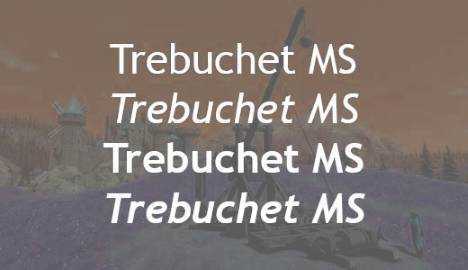
Reef
– приятный русский шрифт, имеющий скругленные границы. Очень подходит для сайтов использующих скругленные линии. Его плюсы в простоте и конструктивности. Также шрифт является свободным для пользователей
Cyrillic Old
– симпатичный шрифт с нотками древнеславянской письменности
Gost
– один из лучших шрифтов для работы с чертежами в программе AutoCad и во всех подобных программах.
Uni Suns
– отличный шрифт, не имеющий засечек. В данном шрифте используются исключительно заглавные буквы. Дизайнер – Святослав Симов (Компания Fontfabric).
Helvetica
– в нашей современности данный шрифт использует любой дизайнер. Шрифт представляет класс нео-гротеск. В арсенале имеются как математические, так и псевдографические символы. Helvetica трудится над разработкой логотипов BMW, Nestle, Motorola, Toyota, Samsung и т.д. Данный шрифт заслужил почетное звание самого перспективного.
Panton
– шрифт имеет 34 начертания с большим набором иконок. Шрифт является достаточно редким, но очень интересным по наполнению.
Open Suns
– шрифт 14-ти начертаний. Достаточно часто используется в дизайне интернет — сайтов. Разработчик – Стив Мэттисон. Отличается дружественной внешностью и удобочитаемостью для мобильных устройств. В основном используется на смартфонах платформы.
Burford
– один из лучших акцидентных шрифтов современности. Лучшее решение для оформления визитных карточек и других компонентов дизайна. Шрифт представлен в 18 начертаниях.
Arkhip
– отличная работа русских дизайнеров – Ивана Климова, Ирины Деменьтевой, Алексея Архипова, Анастасии Бушковой и других. Достаточно редкий, выделяющийся из общей массы шрифт.
Barkentina
– дизайнер – Кирилл Златков. Используемый стиль шрифта – арт-деко. Очень удобен для применения печатных материалов.
K141
– шрифт создан не так давно — в 2014 году. Шрифт без засечек и использует только заглавные буквы.
Cony
– декоративный шрифт с использованием растянутых букв.
Bebas Neue
– русскоязычный шрифт. Особенностью шрифта является растяжка букв в вертикальном направлении.
Danger
– шрифт очень удобен для создания трафаретов.
Iron Russian Edition
– создан на базе известного шрифта Iron. Выделяется своим интересным дизайном.
Nise SEGA Cyrillic
– шрифт оформлен в стиле видео — приставки SEGA.
Movie Letters Cyrillic
– разработан для использования в фильмах для создания титров.
Neon
– отлично подойдет для проектирования вывесок магазинов, баров и т.д. Шрифт выполнен в неоновом стиле.
AC Line
– качественный шрифт для использования в чертежах.
Tkachevica
– действительно красивый шрифт пиксельной тематики.
Capitalist
– жирный шрифт. Напоминает шрифты советского времени.
Lloyd Serif
– необычный шрифт с закругленными буквами.
Illusing Grotesque
– красивый, стильный, тонкий шрифт с засечками.
Ralev
– симпатичный шрифт с закругленными буквами.
Как мы видим, разновидностей удивительных и нестандартных шрифтов — большое количество. Выбор за Вами.
owro.ru
Красивые печатные буквы русского алфавита для оформления
Предлагаем вам красивые печатные буквы русского алфавита для оформления праздника, Дня Рождения, декора стен в детской комнате, для обучения детей буквам. Буквы можно распечатать на цветном принтере, либо воспользоваться черно-белым шаблоном букв и разукрасить готовые буквы вместе с ребенком. Черно-белые буквы можно распечатывать на цветной бумаге или картоне. Нажмите на букву — она откроется в полном размере, после чего ее можно распечатать. Также все представленные алфавиты доступны для скачивания отдельными архивами.
Черно-белые печатные буквы русского алфавита. Скачать архив (Печатные буквы.zip, JPG, 407 Кб)
Красные печатные буквы русского алфавита. Скачать архив (Красные печатные буквы.zip, JPG, 2.2 Мб)
Еще один интересный набор черно-белых печатных букв русского алфавита. Картинки кликабельны. Скачать архив (Черно-белые печатные буквы.zip, JPG, 1.02 Мб)
maminy-sekrety.ru
Шаблоны букв для вырезания
Очень часто в практике школ, детских садов и развивающих центров при подготовке к различным праздникам, для украшения стендов используются шаблоны букв русского алфавита для вырезания из бумаги.
Где и с какой целью могут быть применены шаблоны?
При подготовке тематических вечеров, утренников, детских праздников часто требуется подготовить стенгазету, объявление, оформить выставку детских работ и сделать к ним подписи и т.д. Вся эта организация требует быстрого и четкого оформления с помощью букв русского алфавита. Благодаря шаблонам для вырезания из бумаги эта проблема решается в короткое время. Стоит только приложить шаблон к бумаге нужного цвета, обвести и вырезать, а затем наклеить в необходимое место. В результате готова красивая и ровная надпись.
Где можно достать шаблоны букв алфавита?
Их можно купить в любом канцелярском магазине, однако если дома есть интернет, вы легко можете скачать их совершенно бесплатно с нашего сайта, распечатать и использовать в работе. Таким образом, шаблоны букв для вырезания из бумаги будут полезны, учителям, воспитателям детских садов и развивающих центров.
Однако это далеко не все применение шаблонов алфавита. С их помощью родители могут самостоятельно научить ребенка читать, заинтересовать изучением букв. Вместе с ребенком вы можете вырезать буквы из бумаги, наклеивать на основу или на кубики, составлять слова. Малыш может вырезать буквы из бумаги того цвета, какой он захочет. Так дети лучше усваивают материал, запоминают алфавит, с удовольствием учатся читать и писать.
Шаблоны для вырезания можно использовать для аппликаций. Малыши учатся аккуратно наклеивать вырезанные буквы на бумагу, тренируют усидчивость, внимательность. Если вы занимаетесь с детьми дошкольного возраста, следует соблюдать технику безопасности. Лучше не давать ножницы в руки маленьким детям: буквы вырезают взрослые, а наклеивать могут дети. Вместе с малышами благодаря шаблонам можно готовить праздничные открытки для родственников, поздравления, украшать и подписывать подарки.
Материалы для скачивания
Скачать бесплатно шаблоны букв для вырезания можно здесь.
Вы также можете скачать синий алфавит со знаками препинания и цифрами единым архивом здесь.
Все буквы русского алфавита со знаками препинания и цифрами.
Шаблоны букв русского алфавита на прозрачном фоне по мотивам мультфильма «Маша и медведь.»
Чтобы скачать красные шаблоны букв со знаками препинания, нажмите на эту картинку.Нажимайте на картинки ниже, скачивайте и распечатывайте нужную Вам букву:
Итак, шаблоны букв русского алфавита могут быть весьма полезны не только учителям, воспитателям, но и родителям, которые занимаются развитием своих детей самостоятельно. Шаблоны используются для подготовки праздничных надписей, как для общественных мероприятий, так и для домашнего пользования. Вырезанные буквы полезно применять на уроках труда в качестве аппликаций, для занятий с дошкольниками, для изучения букв русского алфавита и формирования навыков чтения. Шаблоны можно скачать совершенно бесплатно на нашем сайте, распечатать и использовать в работе по своему усмотрению. Они наверняка помогут вам успешно подготовить детей к школе, развить интерес к знаниям.
Похожие статьи
Загрузка…steshka.ru
Красивый почерк алфавит на русском, английском языке (Фото)
Почерк, как умение рисовать, — своего рода искусство. Часто человек не может понять собственного почерка, например, при быстрой диктовке. Сегодня правильное и понятное письмо отходит на второй план, уступая место электронным документам. Но есть ситуации, когда письменная речь должна быть понятна и разборчива. Как исправить почерк и сделать его красивым, расскажет эта статья.
Примеры
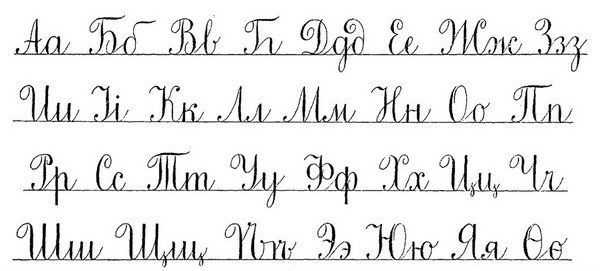
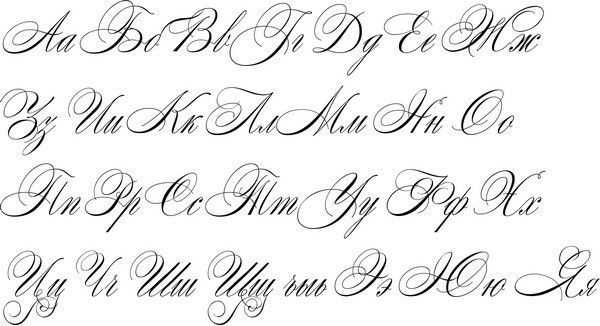
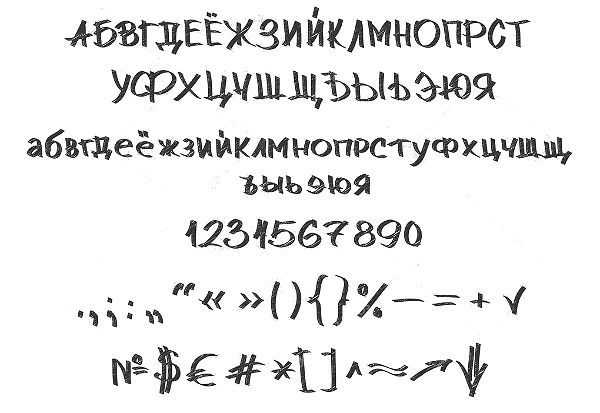
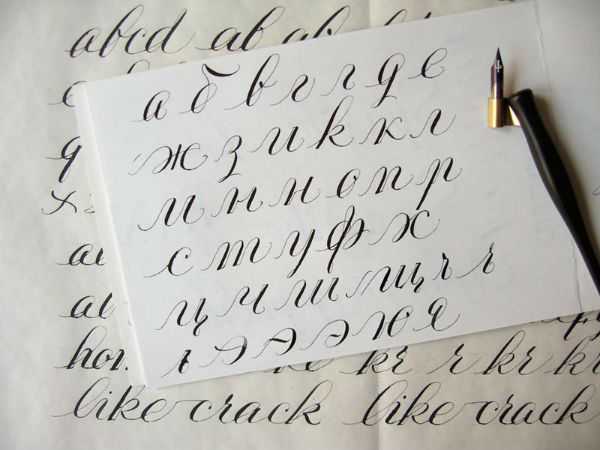
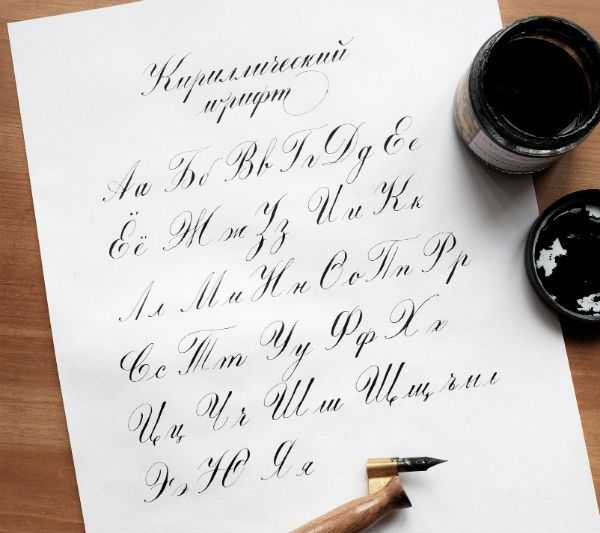
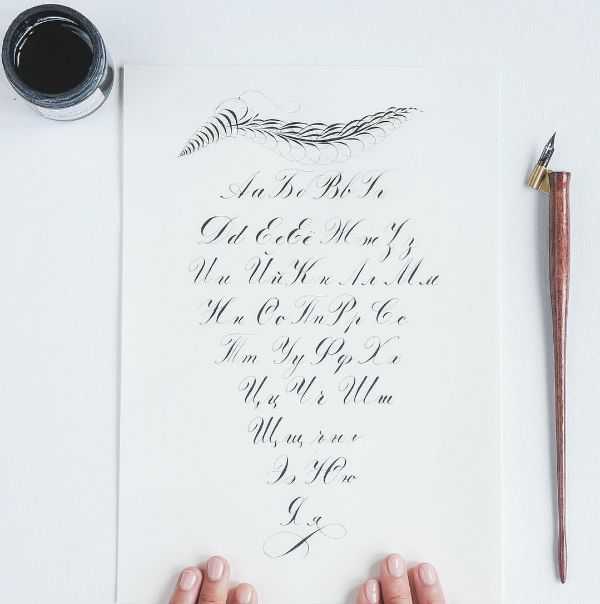
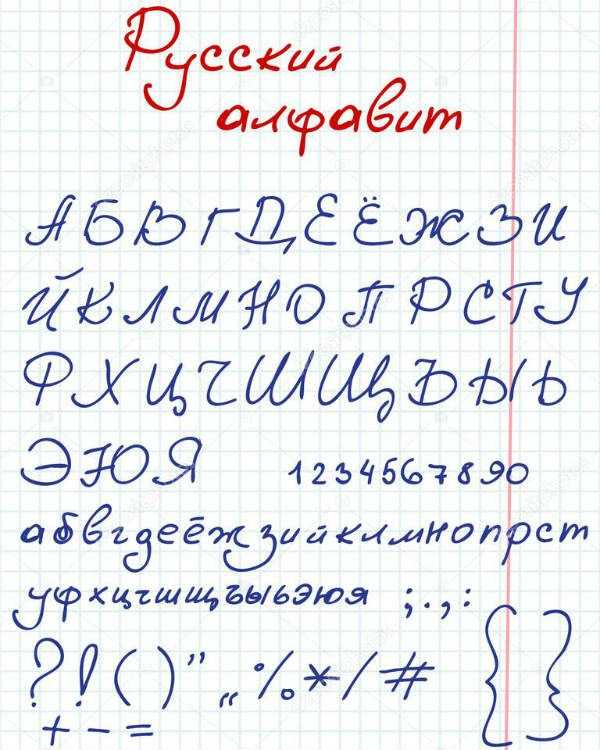
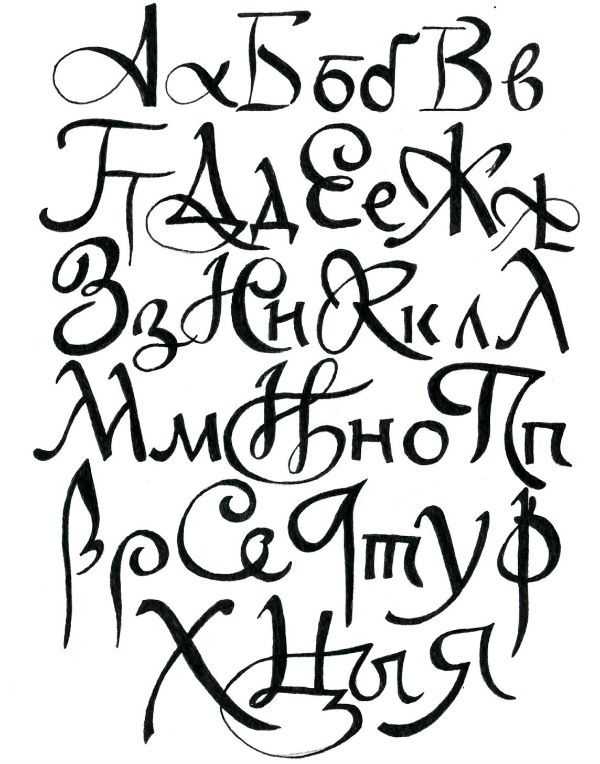
Как добиться красивого почерка
Почерк относится к талантам, ведь он напрямую связан с руками. Красивое письмо — род искусства рисования. Не так давно в школах был специальный предмет, направленный на формирование четкого и красивого почерка. Назывался он каллиграфия.
Сегодня школьников уже не заставляют исписывать страницы с одним крючком, чтобы довести написание до идеала. Программа направлена на освоение навыков письма. При этом красоте и аккуратности почерка отводятся последние роли.
Но если за детьми и формированием их почерка следят родители и учителя, то как взрослому человеку научиться писать понятно и правильно? На случай если взрослый человек желает подправить или изменить почерк, существуют несколько полезных советов.
к оглавлению ^Выбор пишущего инструмента
Удобный пишущий инструмент — ключ к красивому почерку. Не так важно ручка или карандаш. Важно то, что пишущий инструмент удобно лежит в руке и позволяет пользоваться им, не напрягая руку.
к оглавлению ^Посадка при письме
Правильная посадка при работе с письмом помогает не ощущать дискомфорта. Спину нужно держать прямо, а лист, на котором пишется текст, следует расположить под удобным для написания углом.
к оглавлению ^Прописи
Главный совет по улучшению почерка — заново прописать задания в школьных прописях. Они помогут вспомнить о правильном написании соединений между буквами и попрактиковаться в их отработке.
к оглавлению ^Практика
При выработке стиля почерка важно помнить, что постоянная практика позволит лучше запомнить правильное написание всех буквенных элементов. Важно стараться писать чаще и внимательно следить за выполнением написания. К примеру, если не получается написание отдельного элемента буквы или соединение, стоит выписать его на отдельный лист и прописывать до тех пор, пока не получится удовлетворительный результат.
к оглавлению ^Неторопливость
Не стоит ожидать, что почерк улучшится через час сидения за прописью. При работе над почерком важно делать работу вдумчиво и не торопясь. Если не нравится получившийся результат, стоит над ним поработать еще и сравнить с тем, что было ранее. Прогресс в работе может наступить как через неделю, так и через несколько месяцев.
к оглавлению ^Фантазия и шрифты
При работе над написанием стоит подключить фантазию или взять за образец понравившиеся прописные шрифты на компьютере. На специальных сайтах много картинок с прописными буквами. В интернете можно найти изображение с понравившимся шрифтом. Возможно, идея дополнить собственный стиль письма длинными росчерками или изящными завитушками, поможет при работе над красотой и стилем почерка.
к оглавлению ^Смена пишущего инструмента
После освоения одного инструмента стоит попробовать другие приспособления. Если использовалась шариковая ручка, стоит практиковать маркер или перьевую авторучку. Это важно чтобы выработанный почерк не менялся при использовании разных по своей конфигурации инструментов. Таким образом, можно отрегулировать нажим на бумагу и удобный хват для каждого типа ручки или карандаша.
к оглавлению ^Написание иностранного алфавита
Освоение прописных иностранных букв помогает при внесении правок в собственный почерк. Начать стоит с азов — английский алфавит, написанный красивым почерком, выглядит в достаточной мере похожим на русский, что помогает при проработке проблемных мест на ассоциативном уровне.
С помощью таких несложных советов можно полностью изменить свой почерк, сделав его каллиграфическим. Однако правильный почерк для школы не всегда подходит для взрослого человека.
Почерк взрослого человека несет в себе отпечаток личности и ее уникальность.
Если Вам понравилась наша статья и Вам есть что добавить, поделитесь своими мыслями. Нам очень важно знать Ваше мнение!
woman-l.ru
Русский алфавит
Современный русский алфавит происходит от старославянской азбуки. Азбука зародилась приблизительно в 863 году, ее создателями считаются проповедники Кирилл и Мефодий. Многие из букв, учрежденных ими, используются и сегодня в первозданном виде, например, в азбуке церковнославянского языка. Кирилл и Мефодий, в славянском православии, причислены к лику святых, и считаются просветителями всех славян. На сегодняшний день, большинство цифровых шрифтов поддерживают старославянские знаки.
Современный русский алфавит:
А Б В Г Д Е Ё Ж З И Й К Л М Н О П Р С Т У Ф Х Ц Ч Ш Щ Ъ Ы Ь Э Ю Я
Еще более ранним прародителем русского языка является глаголица. Глаголица считается первой славянской азбукой, начертания которой имеют мало общего с современным русским алфавитом. Однако именно от нее произошла старославянская азбука, а затем и русская письменность.
Ученые считают, что Кирилло-мефодиевская азбука использовалась еще в языческие времена. Однако массовое распространение письменности началось только после крещения Руси князем Владимиром в 988 году. В тот период начали учреждаться учебные учреждения, и зародились процессы популяризации письменности среди населения. Шрифты приобретали более правильные, пропорциональные начертания.
В древнерусской письменности было несколько течений, которые использовались для различных целей, а также разными слоями населения.
Книжная письменность. Устав
Уставная письменность — это одна из форм древнерусской письменности, которая использовалась для написания государственных бумаг и оформления книг любых направлений. Уставной шрифт имел угловатые начертания, каждая буква шрифта визуально вписывалась в прямоугольную или квадратную форму. Со временем появился полуустав, в котором появился наклон, и изменились соотношения сторон символов.
Бытовая письменность. Скоропись
Скоропись, в отличие от уставного шрифта, характеризуется округлыми, витиеватыми формами. В основном она использовалась в быту и в учебных учреждениях. Но не редко, скоропись применялась для составления государственных бумаг (на фото письменный указ Петра I). От других форм древнерусской письменности, скоропись отличает наличие большого количества лигатур и росчерков, часто связываемых между собой. Именно скоропись является прародительницей современного рукописного шрифта.
Древнерусская письменность в разные годы переживала многочисленные трансформации. Ниже мы перечислим изменения, которые имели место в истории и в значительной мере повлияли на современный русский алфавит.
Основные периоды реформ в орфографии
- Изначально, кириллица старославянского языка содержала в себе, предположительно, 43 буквы. Из них 14, в разные периоды, были исключены или заменены по ненадобности. В таком виде алфавит существовал до начала XVII века.
- В 1708-1711, после проведения реформ Петра I, были убраны надстрочные символы. Тогда, кстати, перестала существовать и буква «Й», которую вернули в алфавит только в 1735 году.
- 1917—1918 г., упрощение русской письменности. Из алфавита исключили староцерковные дублируемые буквы, такие как «ять» (совпадала по звучанию с современной «е»), и «фита» (современная «ф»). Соответственно «Днѣпръ» стал «Днепр», а «Ѳеодоръ» стал Федором. Реформы вызвали волну негодования среди известных писателей и деятелей того времени.
ffont.ru
Трафареты букв русского алфавита
- Мой мир
- Вконтакте
- Одноклассники
- Google+
Слово «трафарет» произошло от итальянского слова traforetto, что в буквальном переводе означает «пластинка с дыркой». Отсюда и способ изготовления трафаретов —на любом плотном материале делается текст или рисунок, который потом с помощью краски переносится на любую поверхность. Сегодня мы подготовили для Вас трафареты букв и цифр русского алфавита в нескольких вариантах. Трафарет можно скачать к себе на компьютер, распечатать на бумаге формата А4 и составить любую нужную вам фразу. Обратите внимание, что если вырезать внутреннюю часть буквы, то с помощью трафаретов и любой краски можно нанести надпись на какую-либо поверхность. А если убрать наружные части трафаретов, то из бумажных букв можно составить фразы и слова.
Трафарет печатных букв русского алфавита.
Трафарет печатных букв русского алфавита сделан на основе классического шрифта Times New Roman. Скачиваете трафарет, затем нужные Вам буквы из pdf-файла нужно распечатать на листах бумаги формата А4 (обычная писчая бумага) и составить из них нужную фразу.
Трафарет с печатными буквами: Трафарет букв русского алфавита печатный
Трафарет готических букв русского алфавита.
Следующий трафарет- готическое написание букв русского алфавита. Этот шаблон букв очень популярен на Хэллоуин, ему подобные праздники и как трафарет граффити.
Скачать трафарет готического шрифта: Готический шрифт трафарет
Трафарет букв русского языка. Красивый шрифт.
Следующий трафарет- на основе красивого шрифта Monotype Corsiva. Трафарет отлично подойдет для поздравительных надписей и стихов.
Скачать красивые буквы русского языка : Трафареты букв русского алфавита красивый
Готовые трафареты с поздравительными надписями.
И, напоследок, готовые трафареты надписей.